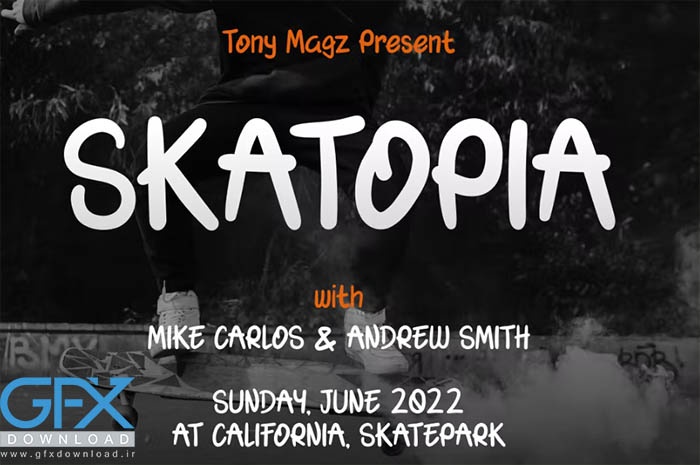
فونت انگلیسی Srat-Sret
فونت انگلیسی Srat-Sret یک فونت زیبا به سبک شهری می باشد. با فونت انگلیسی Srat Sret کار خود را آسان‌تر و سریع‌تر کنید.مناسب برای بازار کتاب های نوجوانان، بازی های ورزشی شدید، پوسترهای رویداد، فونت وسایل مدرسه، پوسترها، عنوان فیلم ها، جلدهای یوتیوب، تصاویر کوچک یوتیوب، جلد صفحات رسانه های اجتماعی و غیره...
• لاتین پایه A-Z و a-z، اعداد، علائم نقطه گذاری